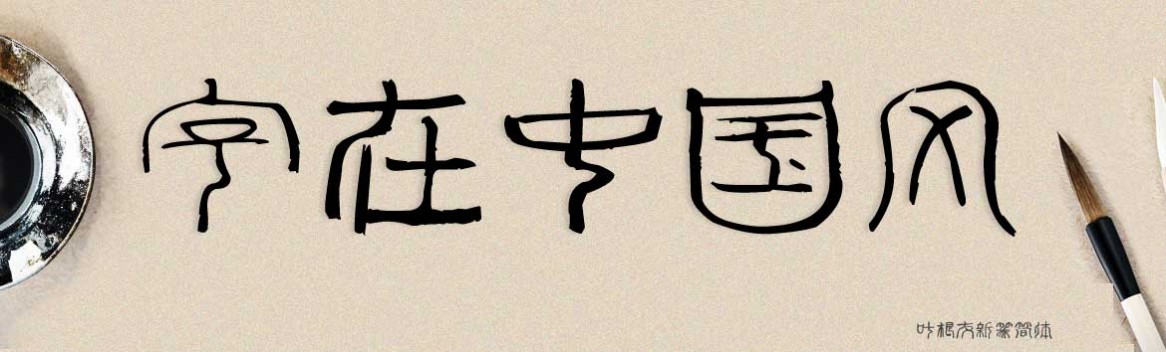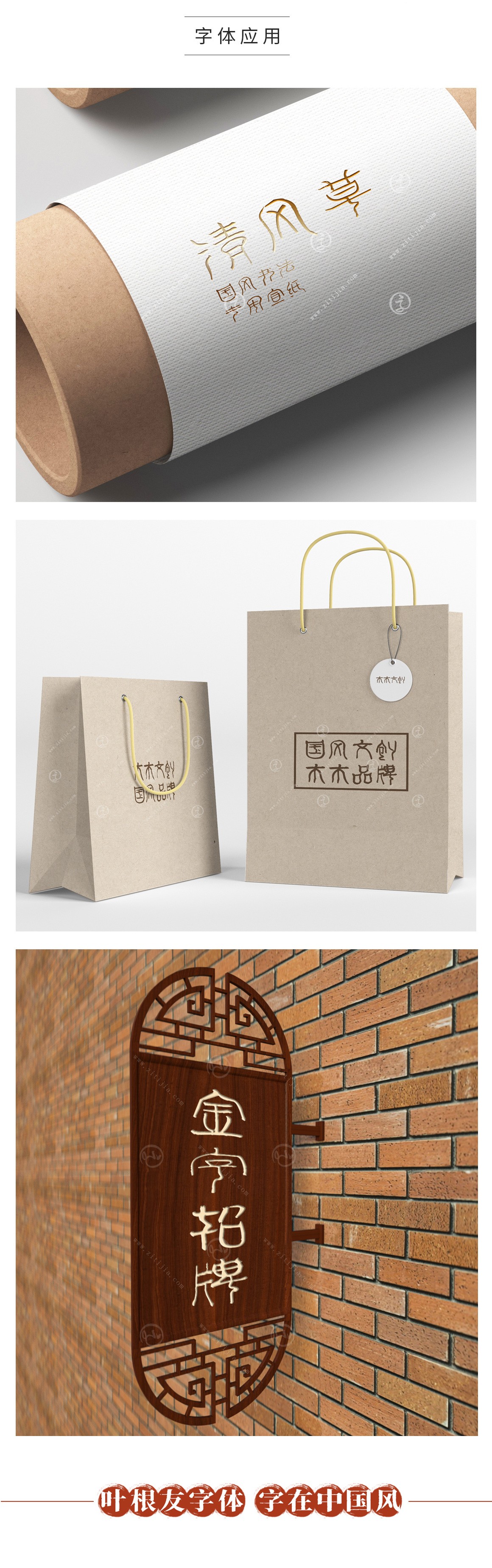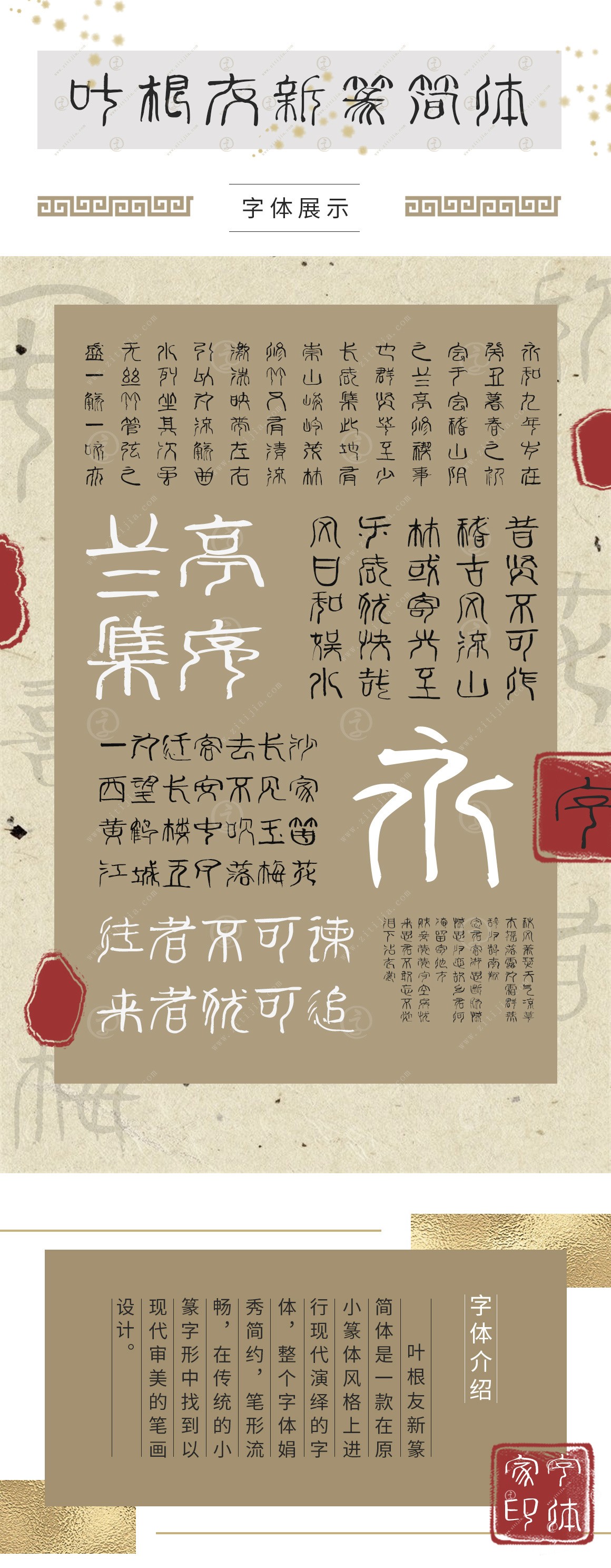
葉根友新篆簡體
字體作者:葉根友
創(chuàng)作年代:2012年
字體字?jǐn)?shù):6763個中文漢字以及其他英文字母和阿拉伯?dāng)?shù)字
字體介紹
葉根友新篆簡體是一款在原小篆體風(fēng)格上進(jìn)行現(xiàn)代演繹的字體,整個字體娟秀簡約,筆形流暢,在傳統(tǒng)的小篆字形中找到以現(xiàn)代審美的筆畫設(shè)計。